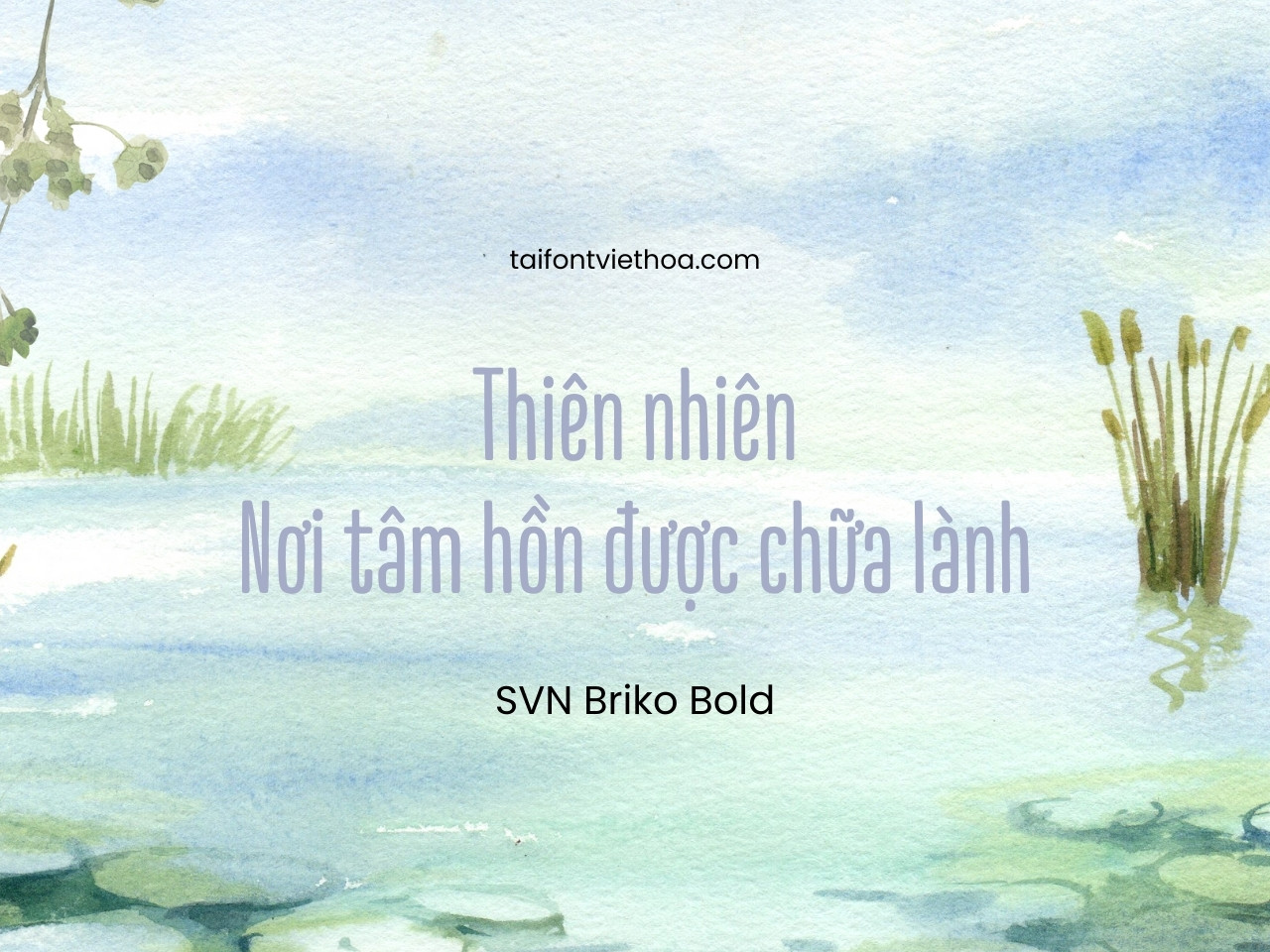
Font việt hóa SVN Briko Bold
Giới thiệu về font SVN Briko Bold – Kiểu chữ sans-serif đậm nét, hiện đại và mạnh mẽ
SVN Briko Bold là phiên bản Việt hóa của font Briko Bold – một kiểu chữ sans-serif mang phong cách đậm nét, hiện đại và rất mạnh mẽ. Font được thiết kế với các nét chữ dày, rõ ràng và sắc nét, tạo cảm giác chắc chắn và năng động, phù hợp cho các dự án thiết kế thương hiệu, quảng cáo và truyền thông số.
Thiết kế sans-serif đậm nét – Ứng dụng đa dạng trong thương hiệu và quảng cáo
SVN Briko Bold sở hữu các nét chữ dày, rõ ràng và cân đối, tạo cảm giác mạnh mẽ và thu hút. Font phù hợp sử dụng cho tiêu đề, banner, logo hoặc poster cần sự nổi bật và ấn tượng. Phong cách thiết kế của Briko Bold rất thích hợp với các dự án công nghệ, thể thao, quảng cáo và thương hiệu hiện đại, năng động.
Ứng dụng lý tưởng: thiết kế logo, poster quảng cáo, banner sự kiện, nhận diện thương hiệu thể thao, website công nghệ và các dự án marketing sáng tạo. Ngành nghề phù hợp: công nghệ, thể thao, giải trí, quảng cáo, thương mại điện tử và startup sáng tạo.